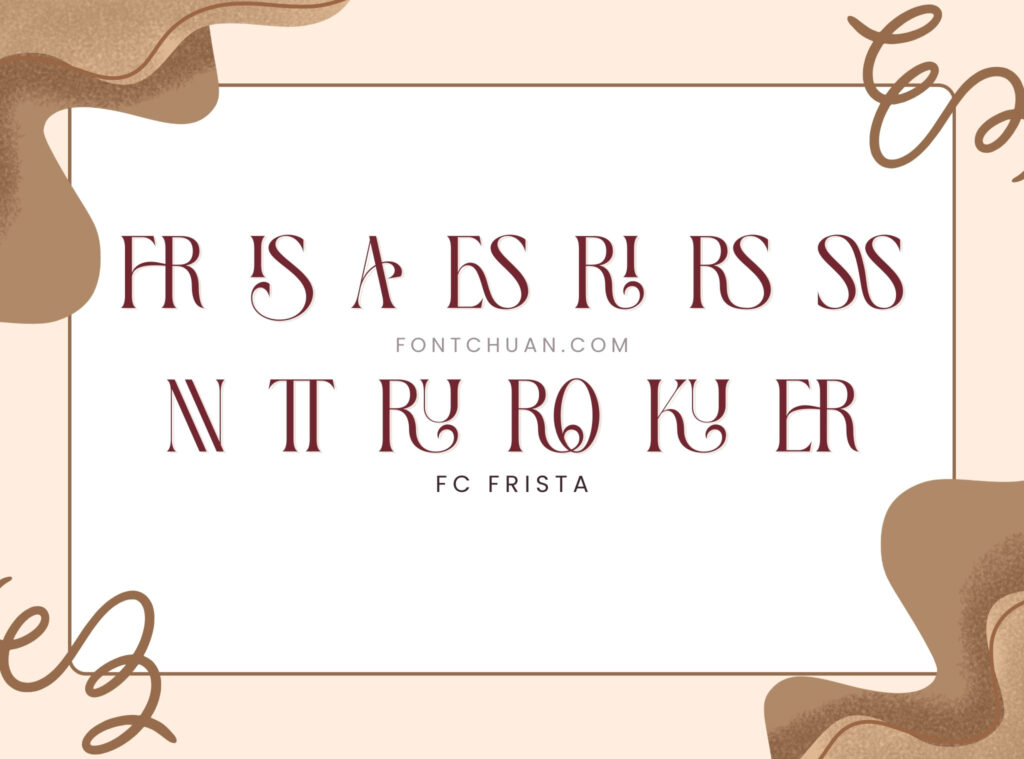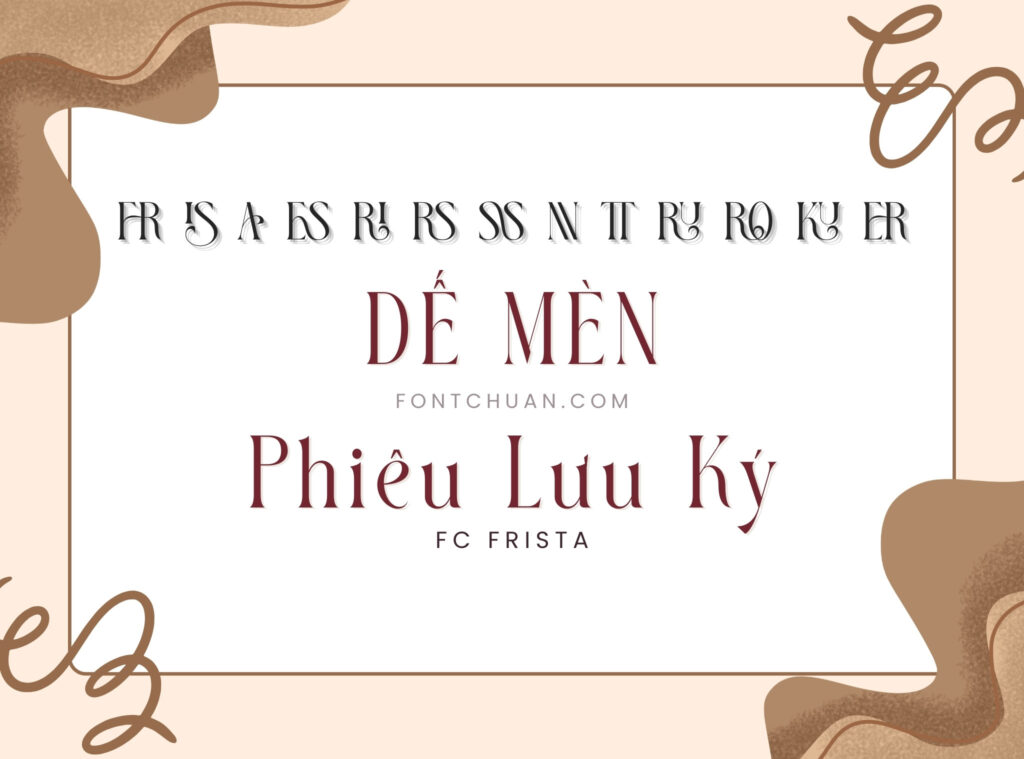
Frista là một kiểu chữ serif hiện đại với các ligature độc đáo, được thiết kế bởi ToniStudio. Font này mang đến sự thanh lịch và sang trọng, phù hợp cho các dự án thiết kế như logo cao cấp, thiết kế biên tập, tạp chí thời trang, thương hiệu mỹ phẩm và các ấn phẩm quảng cáo hiện đại. Frista hỗ trợ đa ngôn ngữ, bao gồm cả tiếng Việt, giúp nhà thiết kế tiếp cận đối tượng rộng rãi.
Về thiết kế, FCFrista sở hữu các đường nét mỏng, gọn và tinh tế, cấu trúc chữ cân đối và phong cách hiện đại, lý tưởng cho nhiều mục đích sử dụng như thiết kế ngành cưới, ẩm thực hoặc bìa sách và các ấn phẩm truyền thông khác.
Font FC Frista có nhiều ligatures (chữ ghép) độc đáo. Bên cạnh đó, khi ứng dụng làm Font ngày Nhà giáo Việt Nam, người dùng có thể tạo ra những thiết kế mang tính tri ân thầy cô, vừa trang trọng vừa hiện đại, phù hợp với các ấn phẩm giáo dục và sự kiện kỷ niệm.